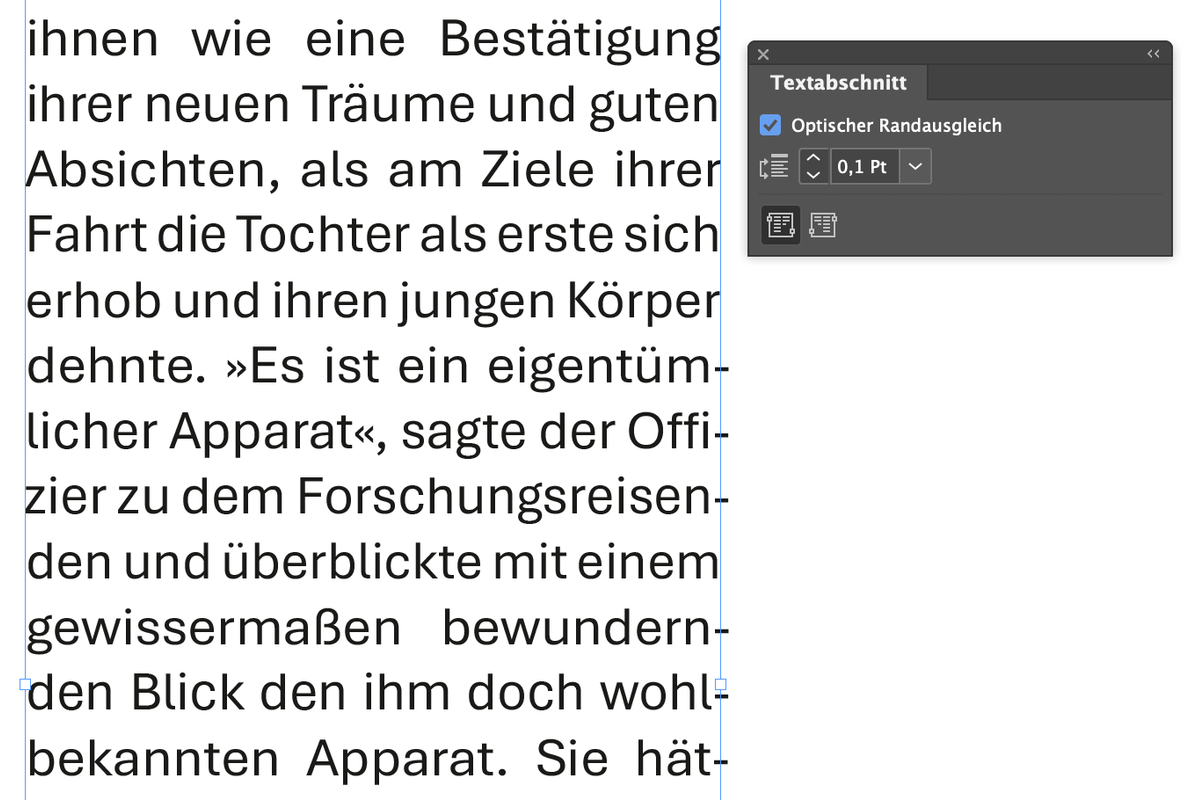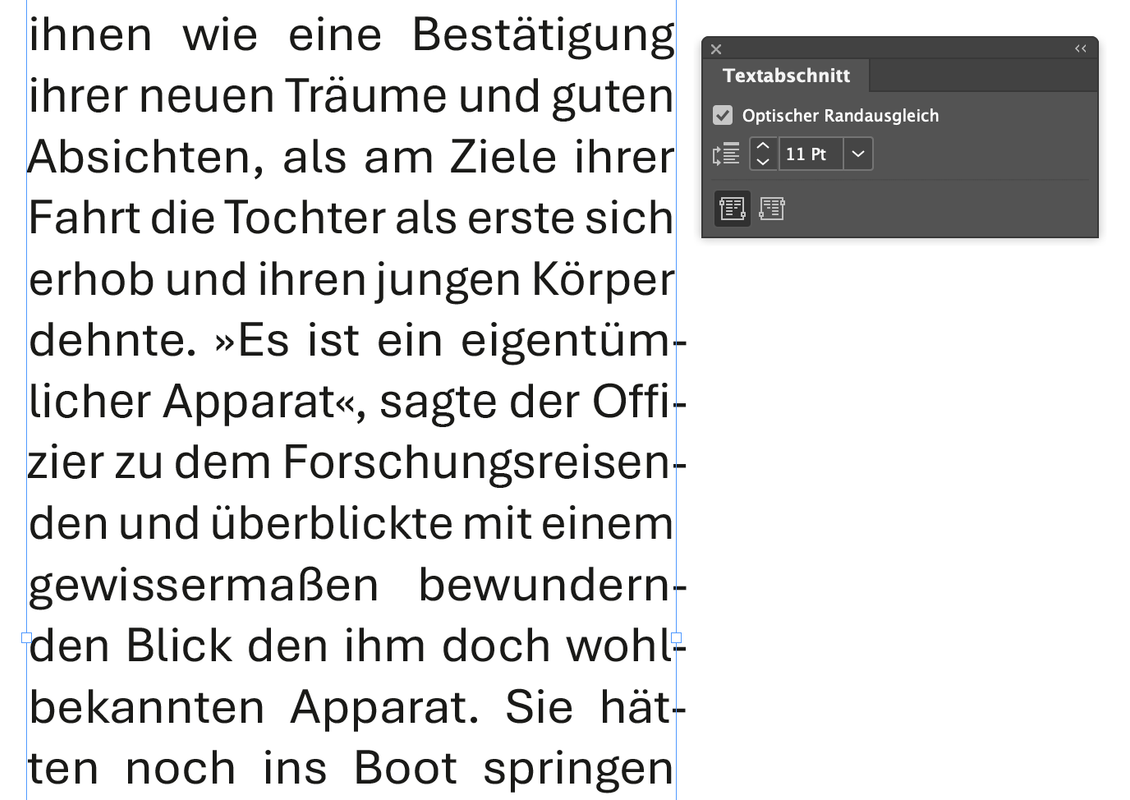
Optischer Randausgleich - Meinungen
Ich greife das Thema mal wieder auf. Mich hat gerade begeistert, wie individuell man den Randausgleich in QuarkXPress justieren kann, selbst in PagePlus X9, einem DTP-Programm für Hobbylayouter, kann man für jedes Zeichen genau einstellen, wie weit es über den Rand gucken soll.
Bietet ID so etwas inzwischen auch? Also den individuell justierbaren optischen Randausgleich?
Soweit ich es überblicke hat sich an den Einstellmöglichkeiten für den Randausgleich in InDesign in den letzten Jahren nichts geändert. Je nach Schrift gibt es immer noch Zeichen die aus meiner Sicht ungünstig weit herausgerückt werden.
Trotzdem ist das Gesamtergebnis im Blocksatz deutlich besser als ohne optischen Randausgleich. Seht ihr das auch so?
Den Schriftgrößen-Wert hab ich noch nie verstanden. Für mich hat die Einstellung dort wenig zu tun mit einem guten Ergebnis, je nach Font und Spaltenbreite muss ich oft ziemlich von der verwendeten Größe abweichende Werte einstellen.
Könnt Ihr erklären, was der Schriftgrößen-Wert in diesem Kontext beeinflusst? Den habe ich diesbezüglich noch nie angefasst. :roll:
Adobe kann es jedenfalls nicht so, dass ich es verstehe :-?
Aptos, 11 pt. In der Vergrößerung sind Unterschiede feststellbar, bei 100 % betrachtet schafft mein Auge das nicht mehr zu unterscheiden. Ein System kann ich auch nicht erkennen, der Überhang ist bei 0,1 pt ähnlich groß wie bei 20 pt.
Dafür ist er wohl am linken Rand größer.
Die Algorithmen sind halt Geschäftsgeheimnis. Das wird Adobe nicht im Detail erklären wollen. Theoretisch soll der Randausgleich so automatisch passend zur Lesegröße erfolgen. Wenn das (speziell bei größeren Graden) komisch aussieht, kann man durch Änderung des Wertes aber gut eingreifen.
… und 0,1 pt sowie 11 pt sind am linken Rand (nahezu) identisch. Deswegen kann ich ja kein wirkliches System erkennen.
Den Faktor versteht glaube ich niemand ... die Frage ist ob Adobe ihn noch versteht.
Generell ist das halt eine On/Off-Entscheidung - bei Lesetext ist das besser als kein Ausgleich.
Schade ist, dass man bei Adobe nicht manuell eingreifen kann, indem am Beginn (oder uach Ende) einer Zeile / am Beginn eines Absatzes ein Kerning "gegen das Nichts davor" einstellen kann – man braucht immer ein unsichtbares Leerzeichen davor, um danach dann einen negativen Wert einstellen zu können der einen Buchstaben kontrolliert nach außen oder innen schiebt. Das wäre bei Titeln etc. viel nützlicher als ein pauschales an/aus, das nur bei Lesetext einen Mehrwert hat.
Der einstellbare Schriftgrößenwert hat theoretisch den Sinn, dass unterschiedliche Schriftgrößen in demselben Textrahmen gemeinsam eine glatte Kante bilden. Das heißt, wenn eine 32-Pt-Überschrift, ein 18-Pt-Einleitungstext und ein Brottext mit 10 Pt zusammen stehen, kann man das Gesamtgefüge entweder an den 32 Pt, den 18 Pt oder den 10 Pt ausrichten. Im ersteren Fall wird der gesamte Text links stärker eingerückt, im letzteren Fall die Überschrift stärker ausgerückt. Wie gesagt, theoretisch – wie gut das in der Praxis funktioniert, hängt von Schrift(mischung), Raster, Größendiskrepanz und im Einzelfall den ausgerückten Zeichen ab.
Was mich dabei stets stört: Die stärker eingerückten Ränder bewirken, dass die Kolumne das Raster verlässt. Ich muss dann den Textrahmen manuell und geschätzt verbreitern, sodass der Text wieder im Raster sitzt. In Zeiten intelligenter Hilfslinien und generell computerisierter Präzision fühlt sich das schwammig, mühselig und »falsch« an, auch wenn es im Druck keinen Unterschied macht.
„When too perfect, lieber Gott böse.“
Nam June Paik – koreanischer Künstler
das hat nicht nur mit wissen und mode zu tun, sondern auch mit technischen möglichkeiten. in indesign ist optischer randausgleich als funktion zwar – soweit ich weiß – seit cs2 verfügbar, aber die möglichkeiten der feineinstellung sind bis heute nicht befriedigend. quarkxpress bietet randausgleich erst seit der neuesten version an; dafür kann man es dort genauer kon?gurieren. bei diversen redaktionssystemen und weniger verbreiteten satzprogrammen, mit denen viele buch- und zeitschriftenverlage arbeiten, gibt es so eine option erst gar nicht. bei allen nicht-digital gesetzten büchern kannst du daher davon ausgehen, dass nur die luxusausgaben über randausgleich verfügen, einfach weil das vor dtp eine scheißarbeit war.
Hallo liebe Typo-Leute,
Ich arbeite im Blocksatz nur mit optischem Randausgleich. Es gibt die Option in den Satzfeineinstellungen, die nutze ich und je nach Schriftart passe ich die Abstände an. Spatzionierung und dort Zeichenformat.  Passiert ist im InDesign wirklich wenig, Affinity ist dort besser. Nur kann man die Daten von Serif nicht in *indd übertragen, was umgedreht zwar geht, aber in der Druckvostufe nur mit absolutem Profiwissen umzusetzen geht (Farbprofile, Ausgabeprofile, Simulation etc. spricht ja eigentlich für Affinity, ist aber sehr zeitaufwändig). Leider